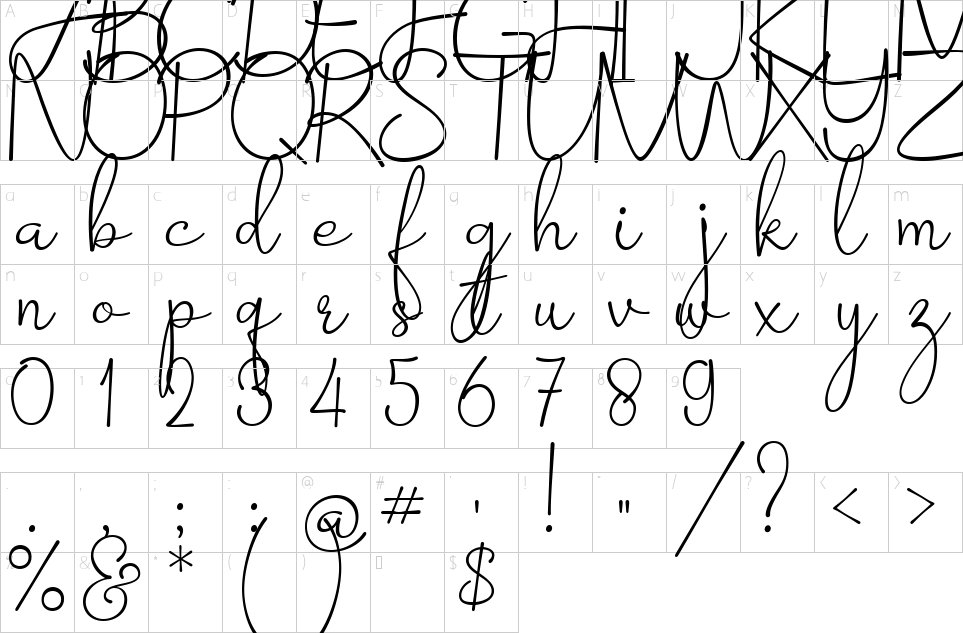
Baixe a Fonte Barokah Signature para Windows e Mac. Esta elegante e sofisticada fonte foi criada pelo Alifinart Studio e já foi baixada mais de seis mil vezes. Com seu design arrojado, a Barokah Signature é ideal para criar gráficos com um toque de luxo e profundidade. Através do seu detalhamento único e estilo inconfundível, esta fonte adquirem um brilho especial às suas criações digitais. Seja você designer gráfico ou profissional de marketing digital, a Barokah Signature é uma escolha inteligente para quem busca um toque de sofisticação em seus projetos.